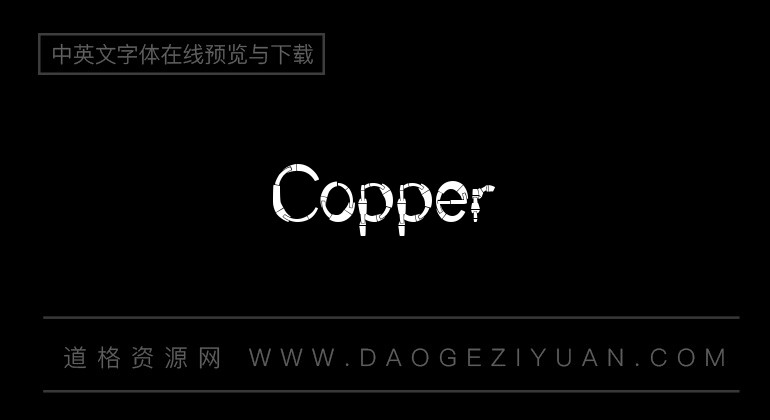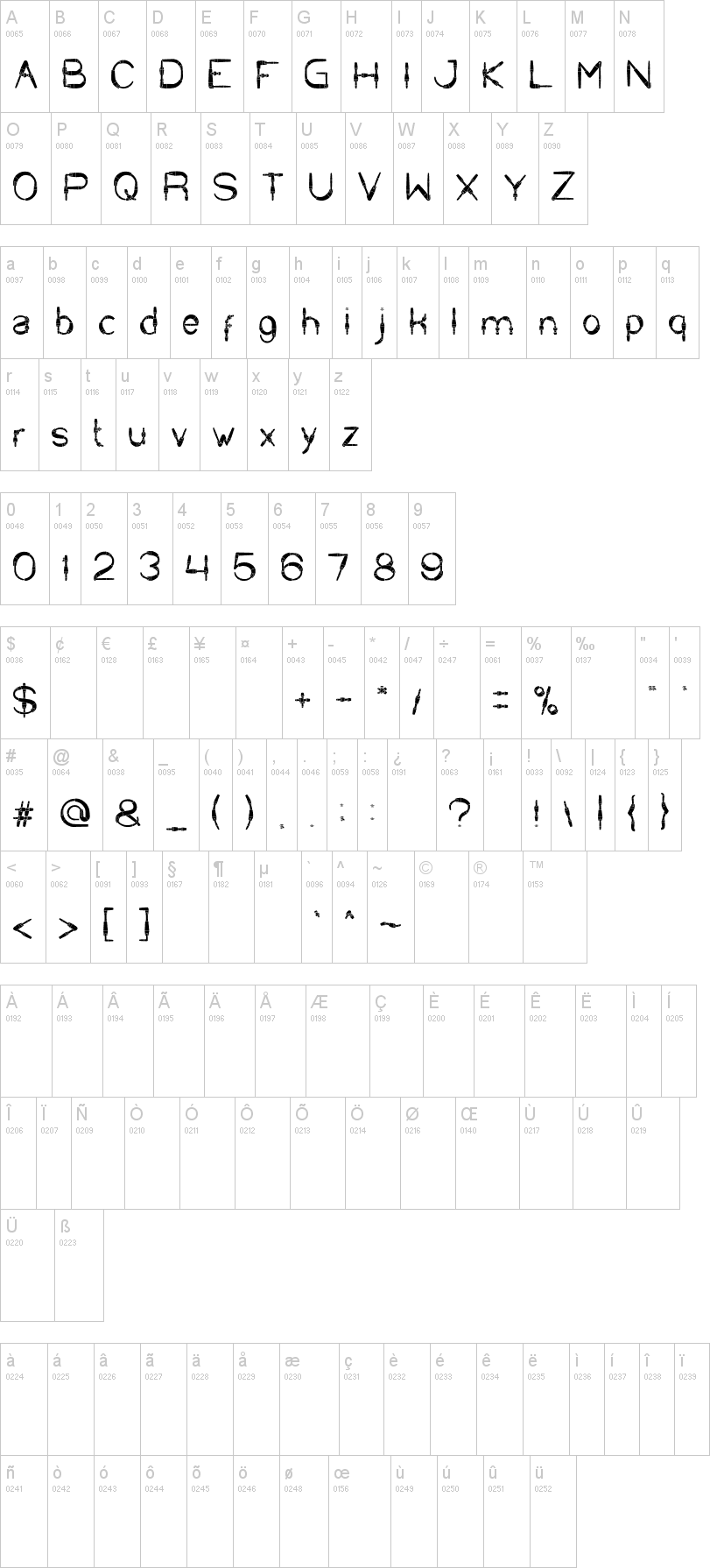
Copper
Copper 字体是一款简约、大气、古典的英文字体,它可以帮助设计师创造出精致而又充满艺术感的设计作品。Copper 字体的笔画粗细恰到好处,字体的结构结实,形成的字体更加清晰,更加美观,更加完美。此外,Copper 字体还具有良好的拉伸性,可以根据设计师的要求,调整字体的粗细度,从而达到更好的设计效果。
Copper是一款非常不错的手写艺术字体,具有很好的视觉感,适合于文化类的宣传设计、商业类品牌的广告和产品包装设计以及个性化文字排版等较多场景。